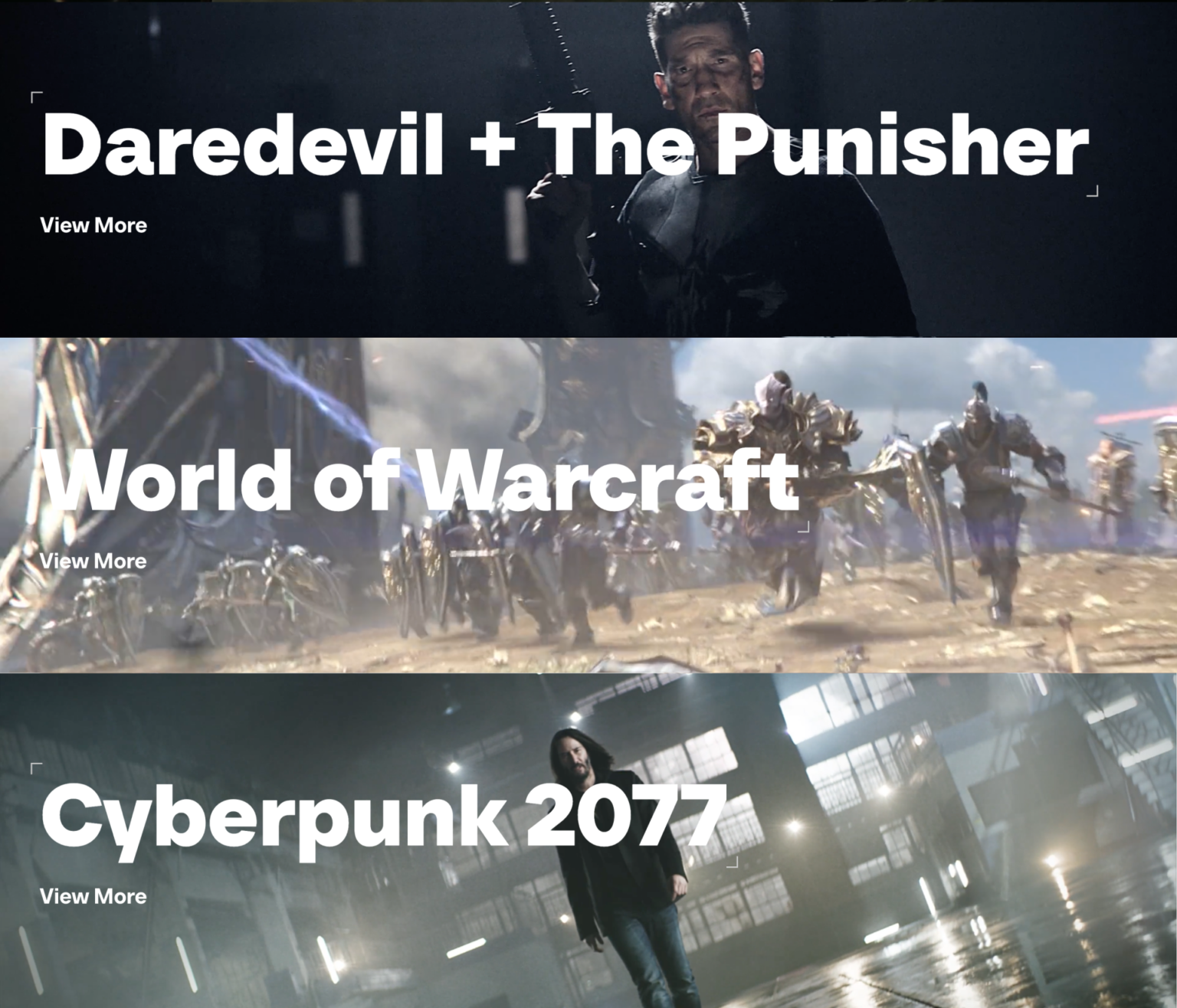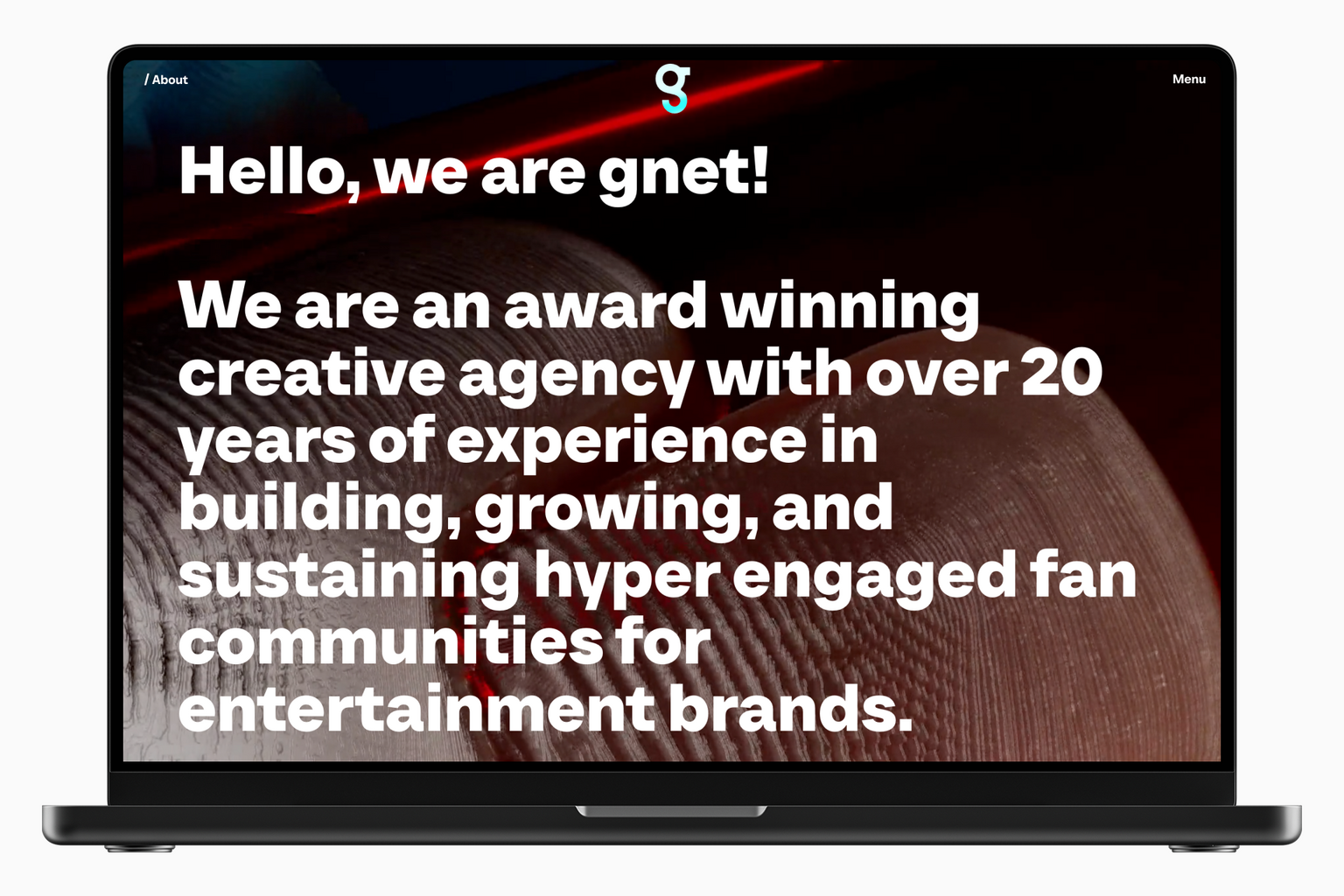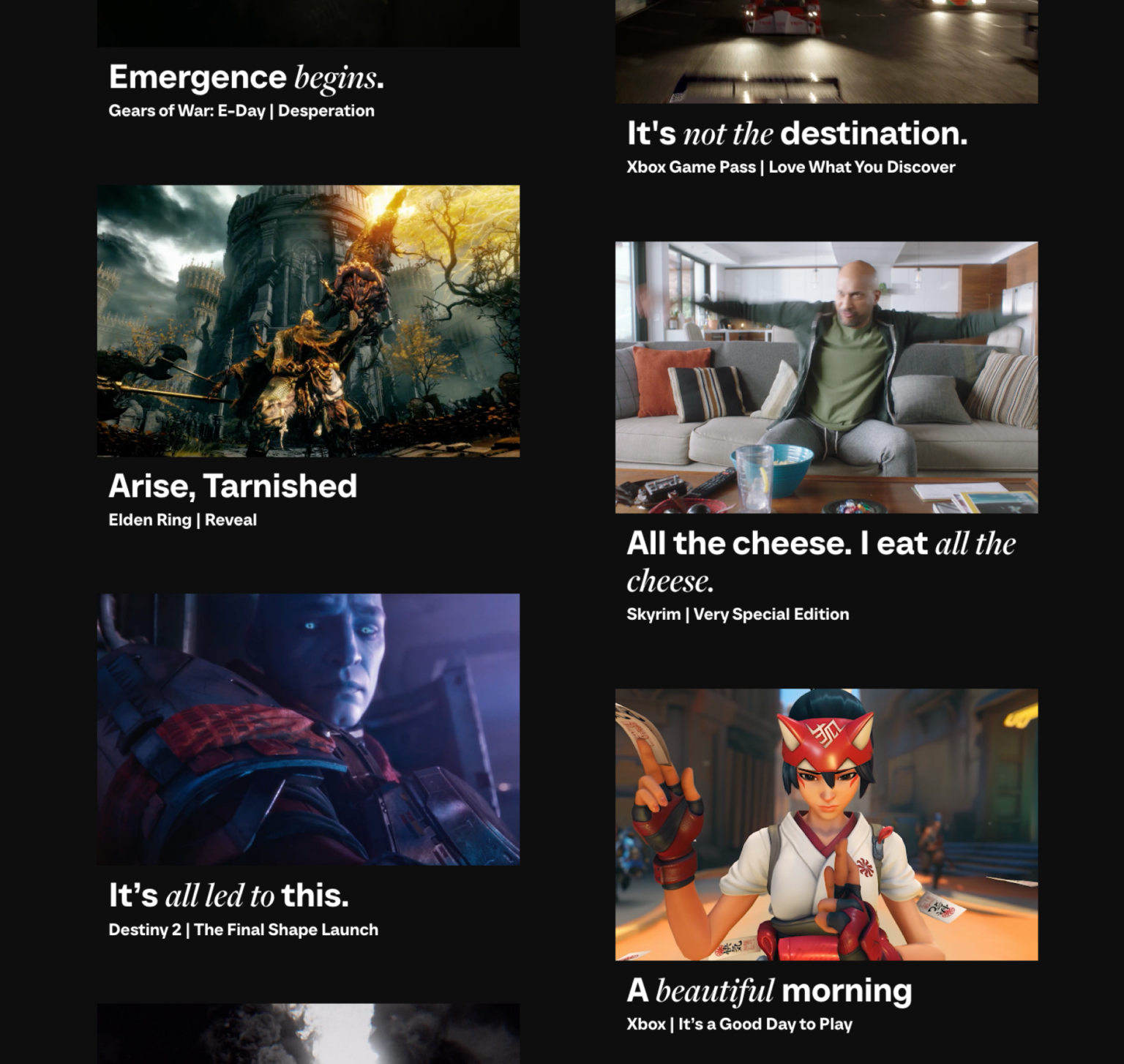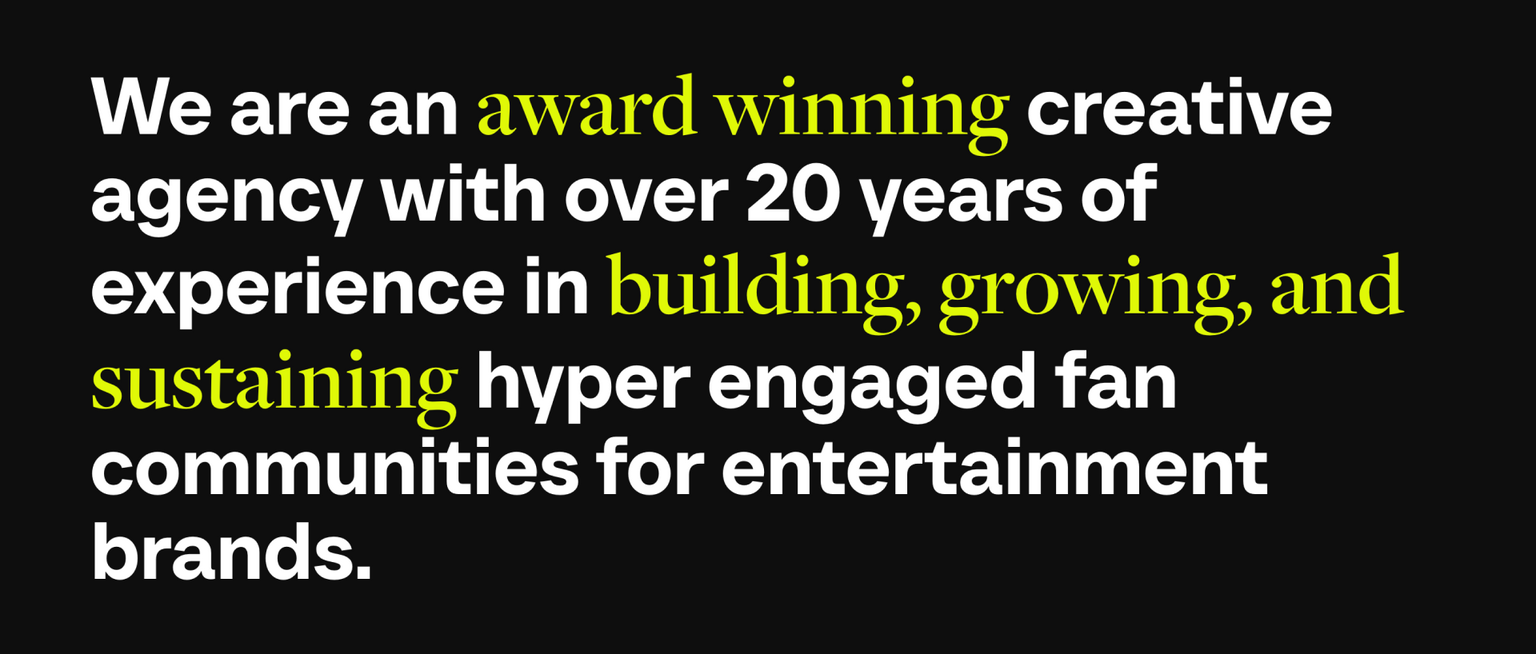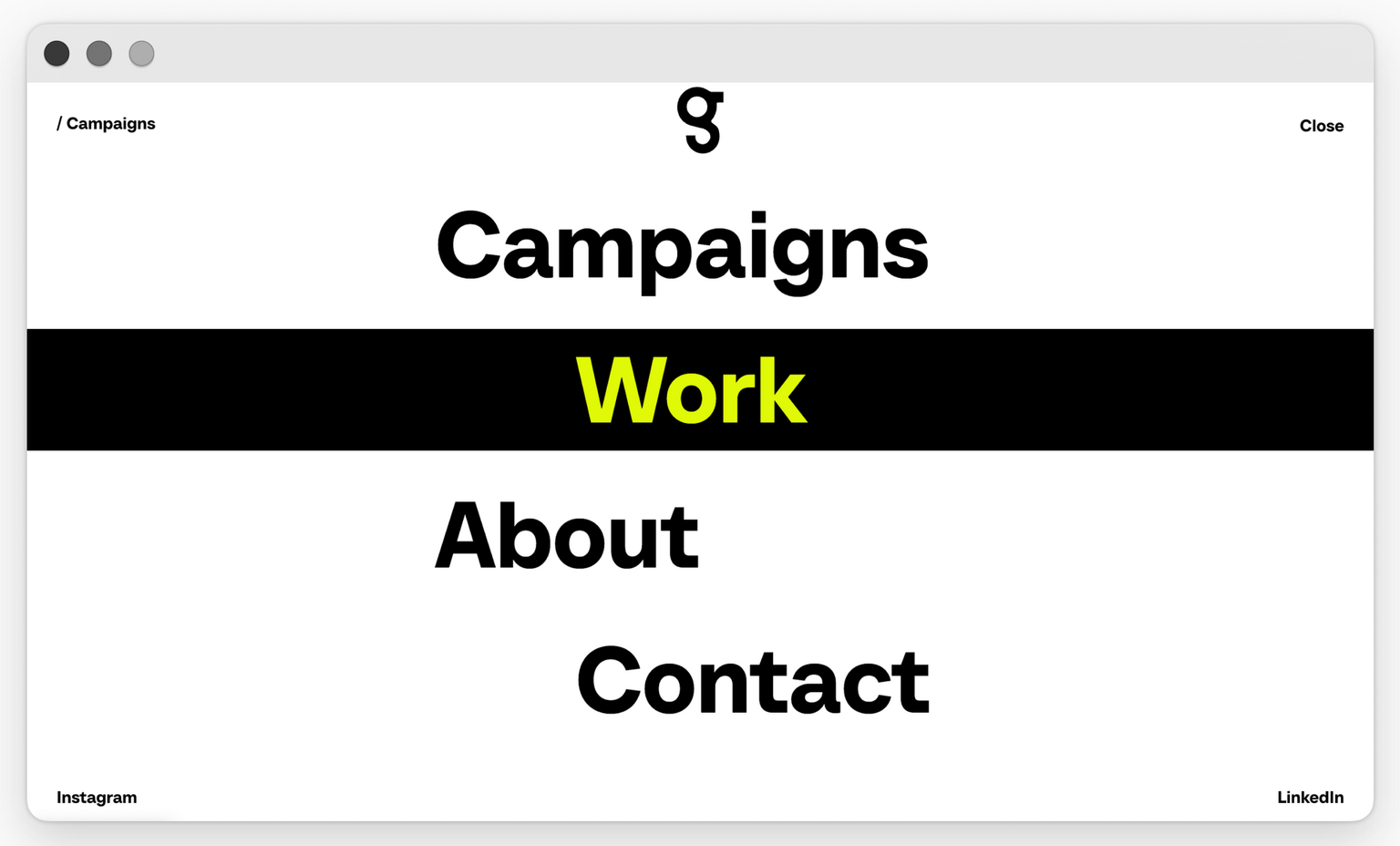
ТТ Неорис (TT Neoris) — теперь часть фирменного стиля компании Gnet.
Gnet Agency — это маркетинговое агентство, которое помогает киностудиям, телеканалам, стриминг-сервисам и другим компаниям из сферы развлечений, таким как Netflix и Disney, находить и объединять поклонников. ТТ Неорис отлично вписался в динамичный дизайн компании и помог придать ему игривое звучание, сохранив при этом лаконичность.